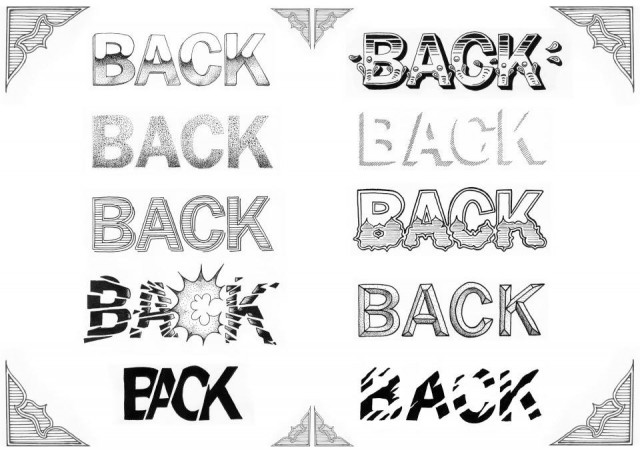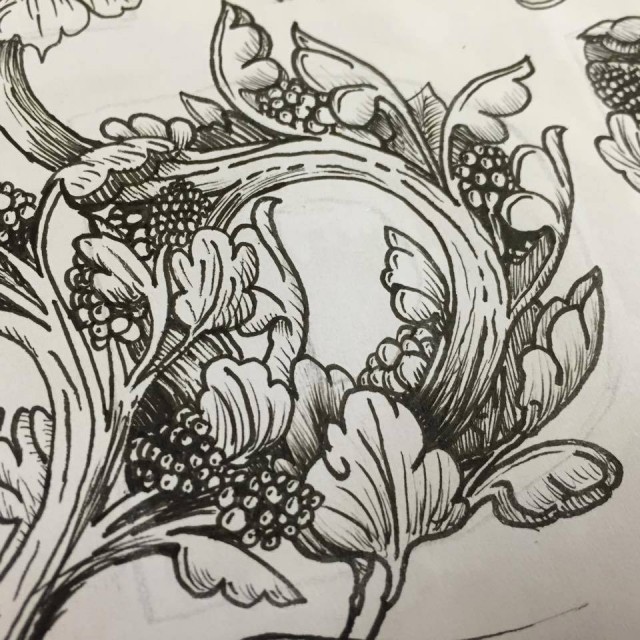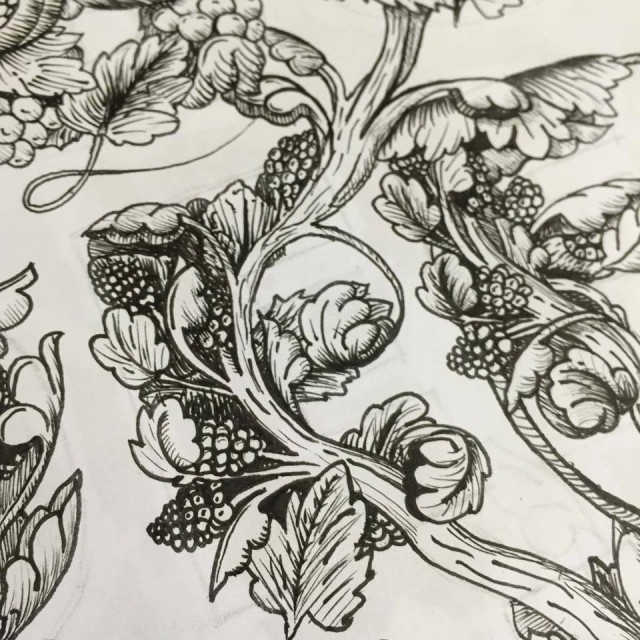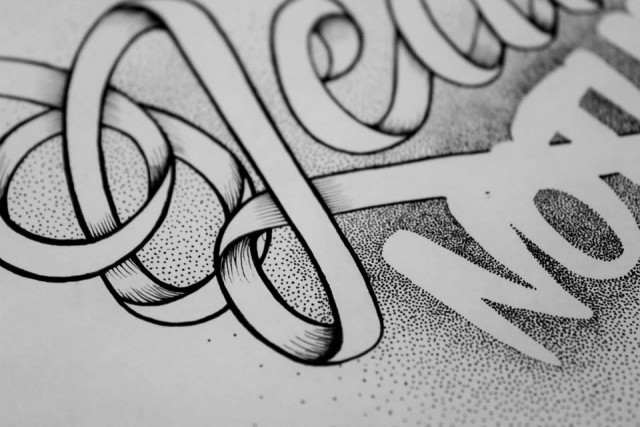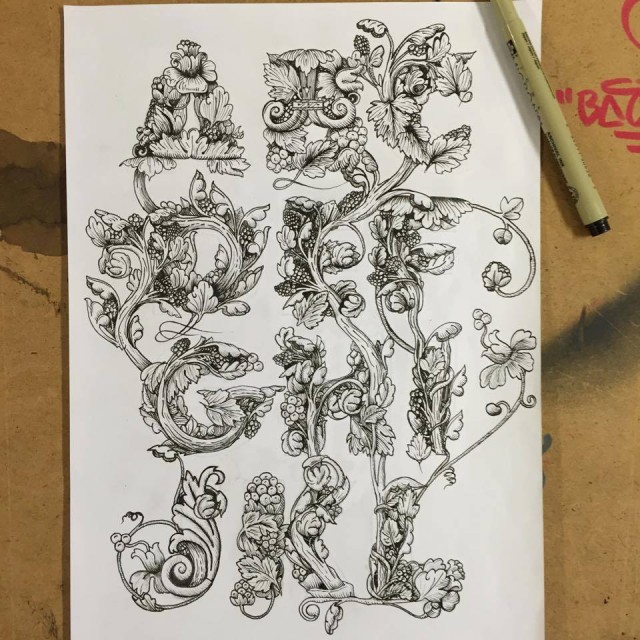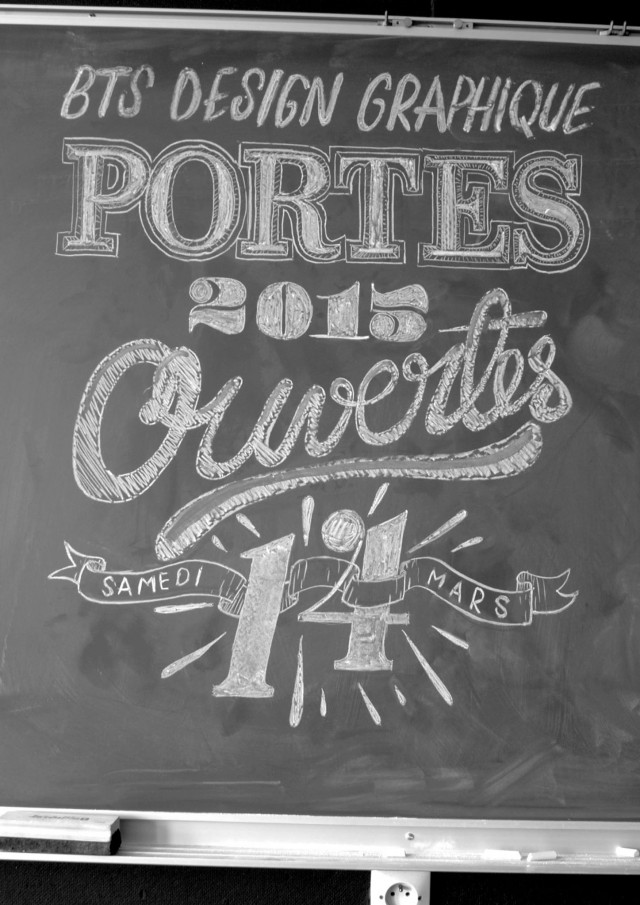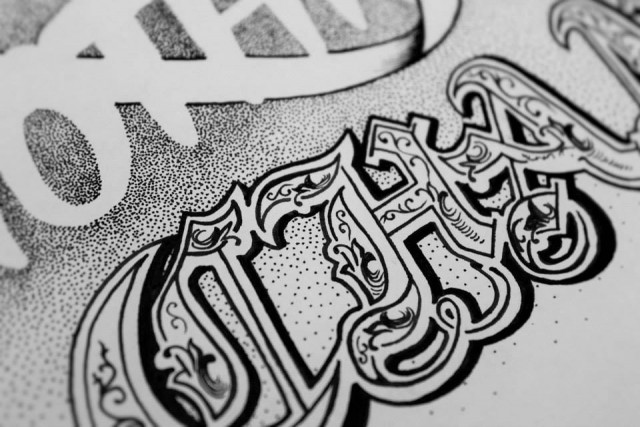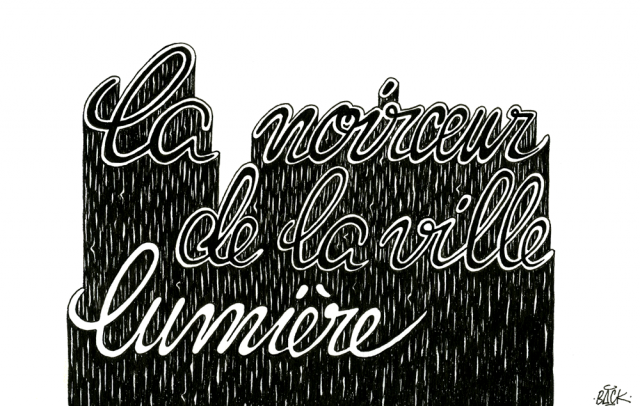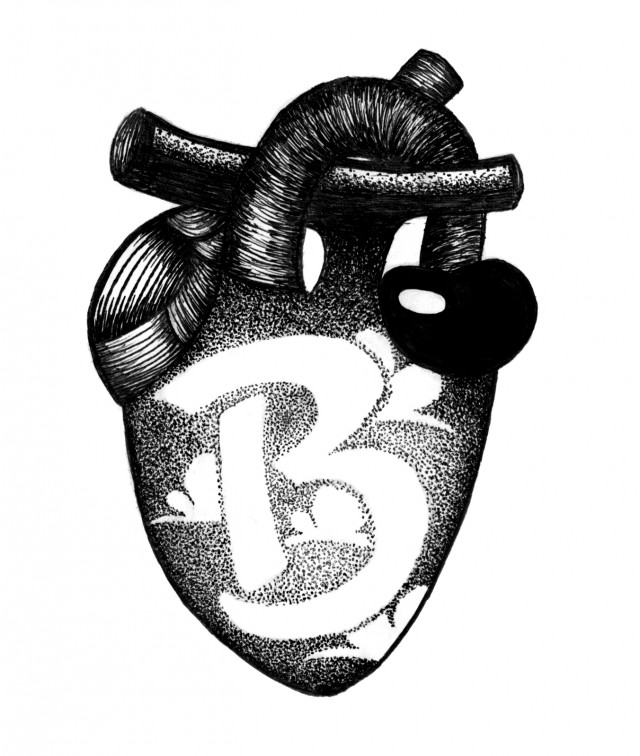
Thomas Lateur est un jeune typographe bisontin de seulemet 21 ans. Bersé dès son enfance dans le monde du graffiti il s’orientera plus tard dans le design graphique. Son but : Donner une peronnalité à ses lettres et créer un impact visuel pour ne laisser personne indifférent.